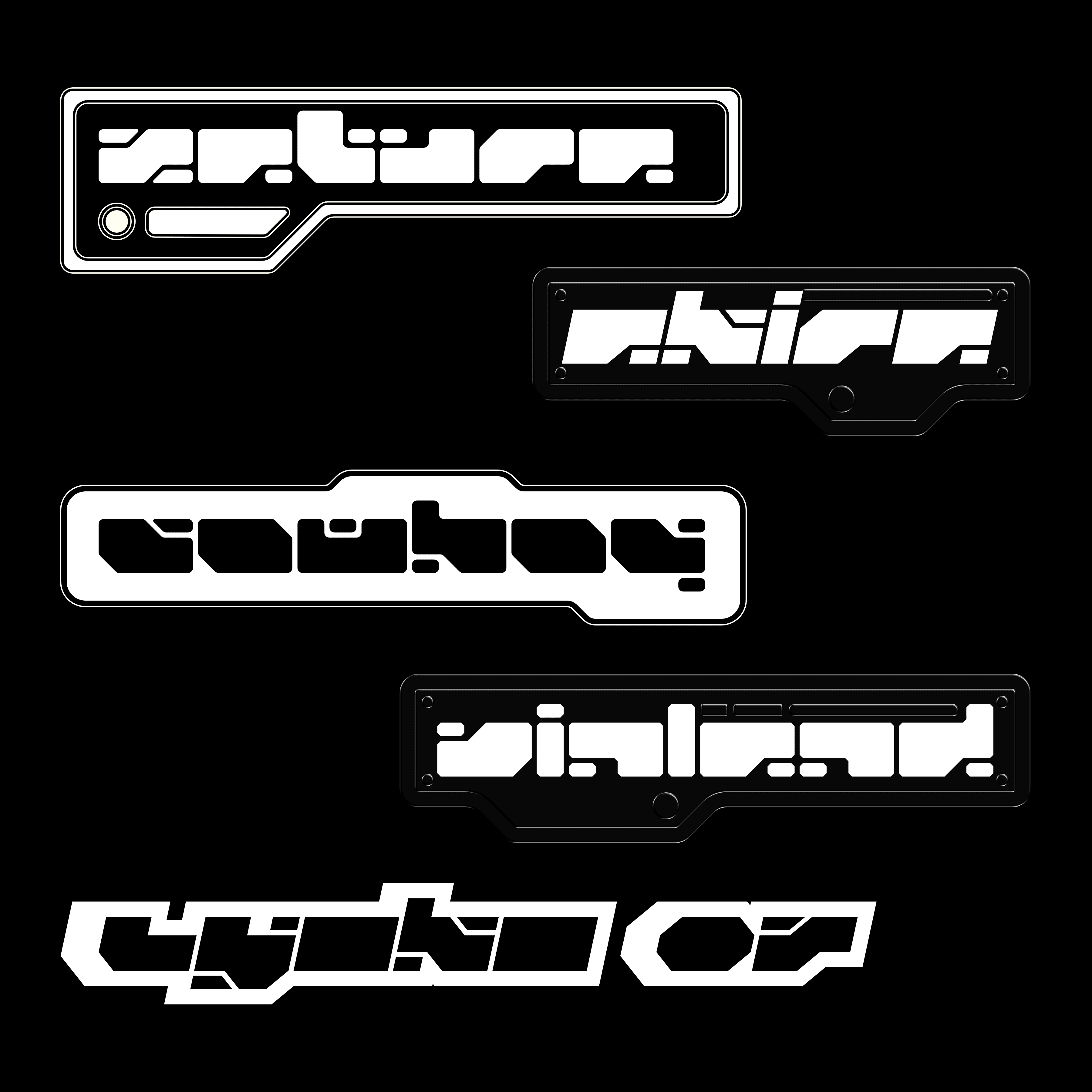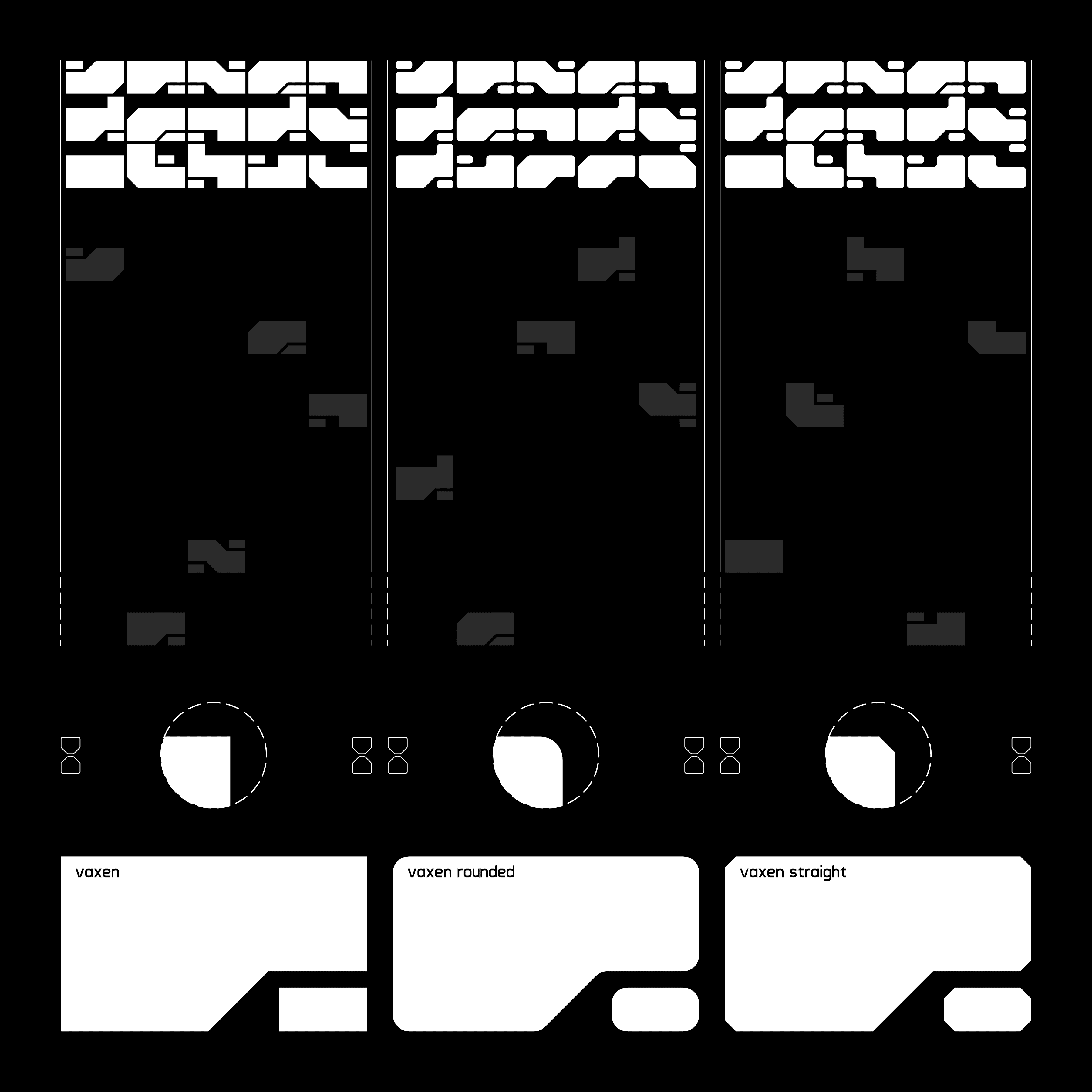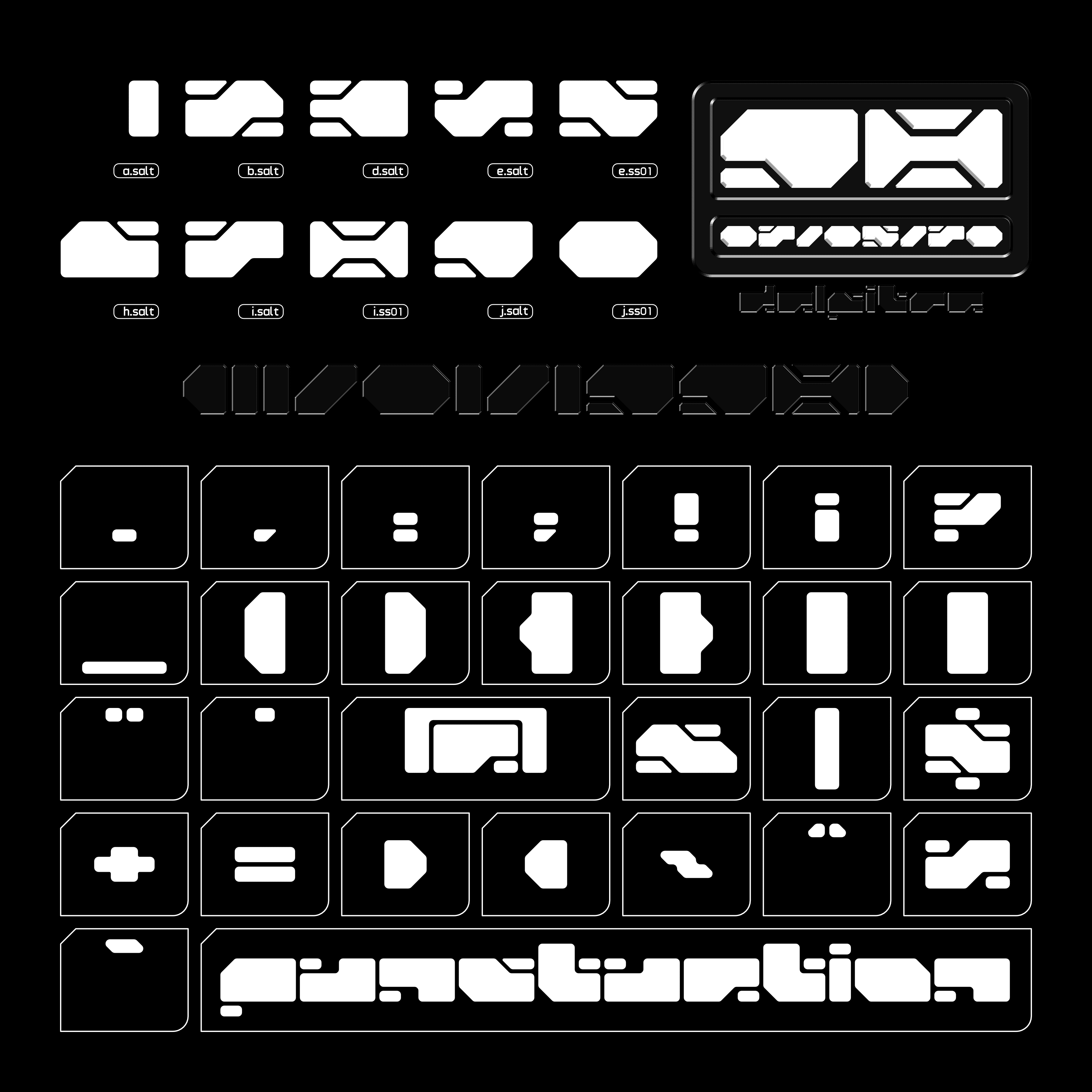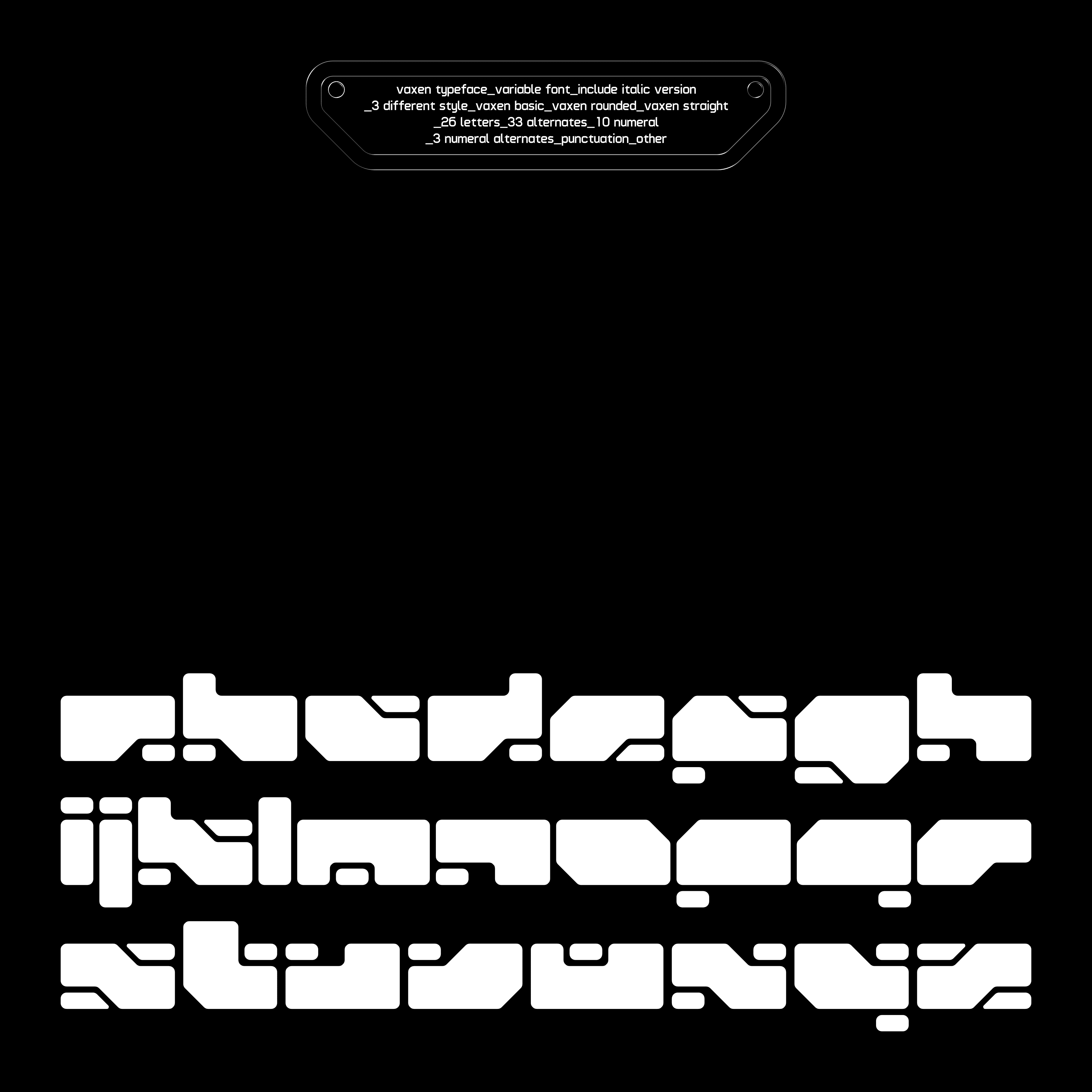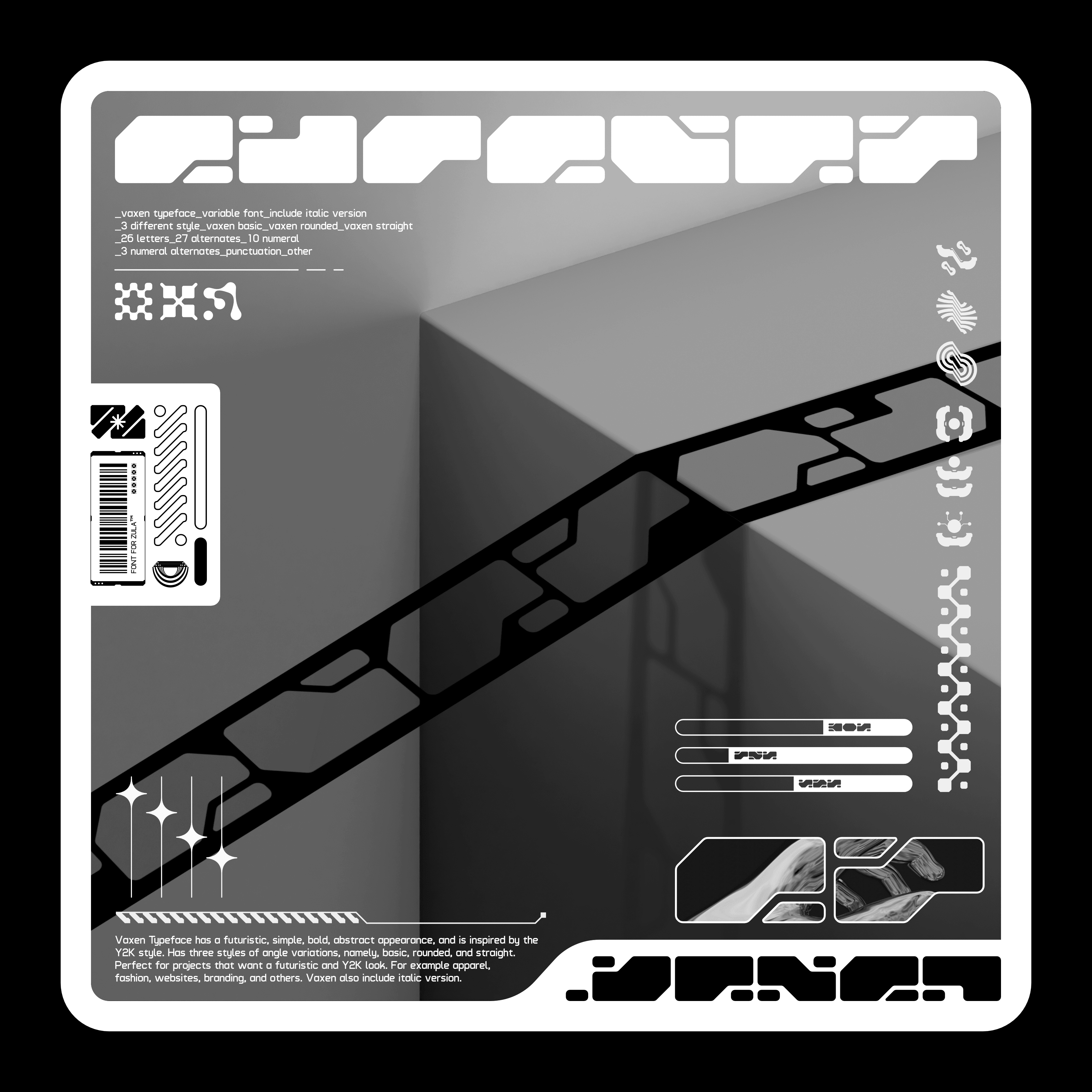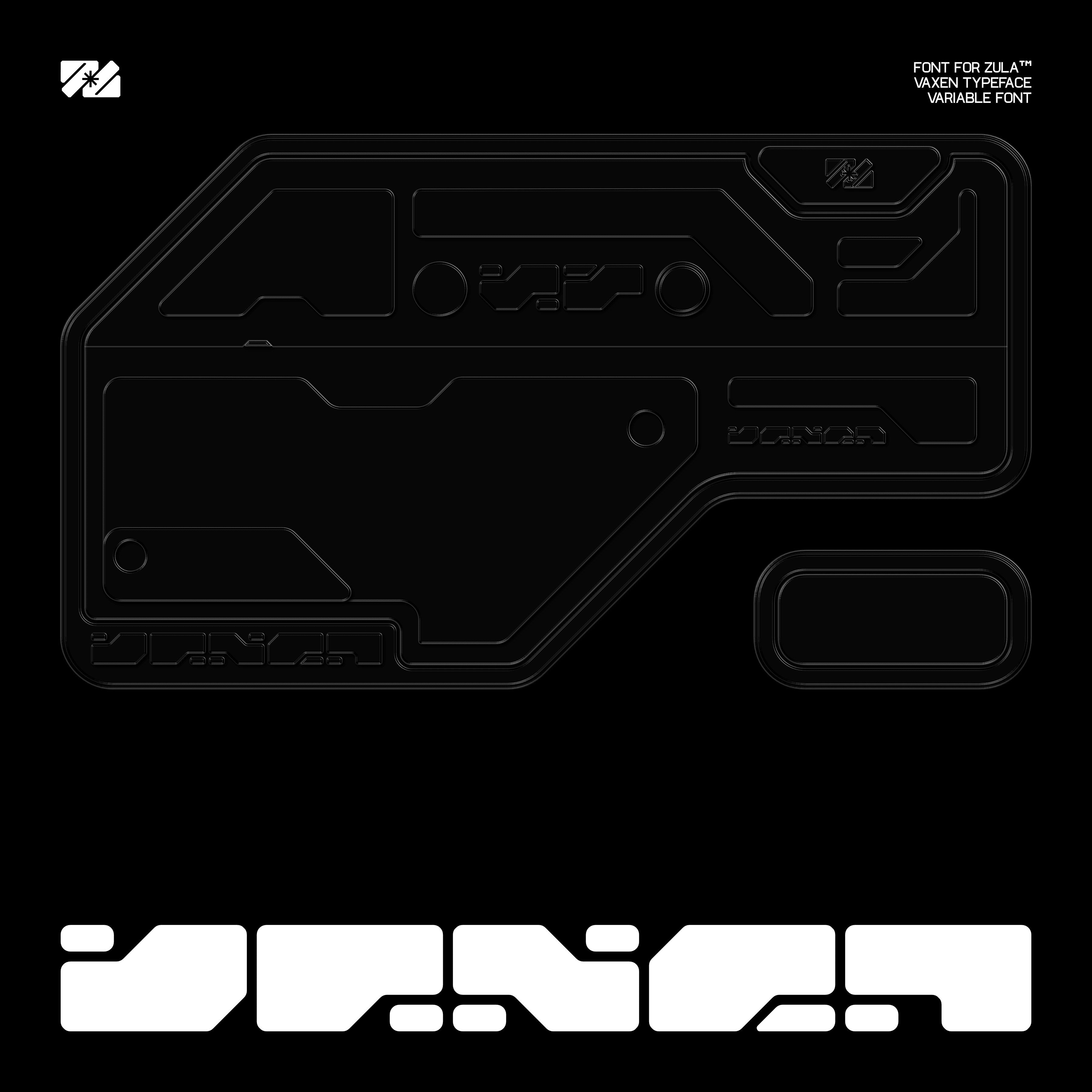
Kiểu chữ Vaxen là một Phông chữ có thể thay đổi có vẻ ngoài tương lai, đơn giản, táo bạo, trừu tượng và được lấy cảm hứng từ phong cách Y2K. Có ba kiểu biến đổi góc, cụ thể là cơ bản, tròn và thẳng. Hoàn hảo cho các dự án muốn có giao diện tương lai và Y2K. Ví dụ: may mặc, thời trang, trang web, thương hiệu và những thứ khác. Vaxen cũng bao gồm kiểu chữ nghiêng
Kiểu chữ Vaxen có:
- 3 phong cách khác nhau
- Vaxen cơ bản
- Vaxen tròn
- Vaxen thẳng
- Kiểu in nghiêng Bao gồm
- 26 chữ cái
- 33 người thay thế
- 10 chữ số
- 3 chữ số thay thế
- Chấm câu
- khác